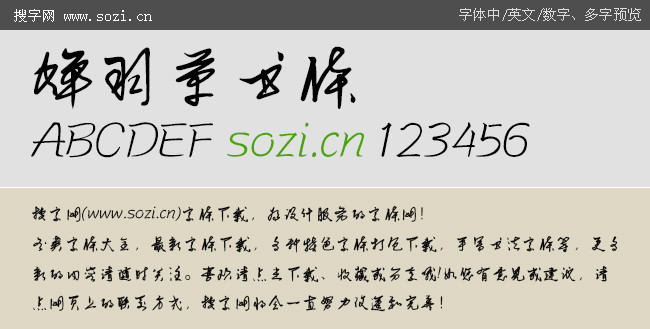
蟬羽草書體
搜字網(wǎng)提供一款蟬羽草書體中文書法字體下載,蟬羽草書體是全新開發(fā)的一款草書字體,該字體運(yùn)筆遒勁有力,奔放縱逸,字里行間內(nèi)蘊(yùn)無(wú)窮,古趣盎然,充滿張力磁性,能夠適用于藝術(shù)設(shè)計(jì)、包裝印刷、簽名設(shè)計(jì)、圖形設(shè)計(jì)等領(lǐng)域。(本字庫(kù)版權(quán)歸王建剛個(gè)人所有,商用需經(jīng)作者許可)